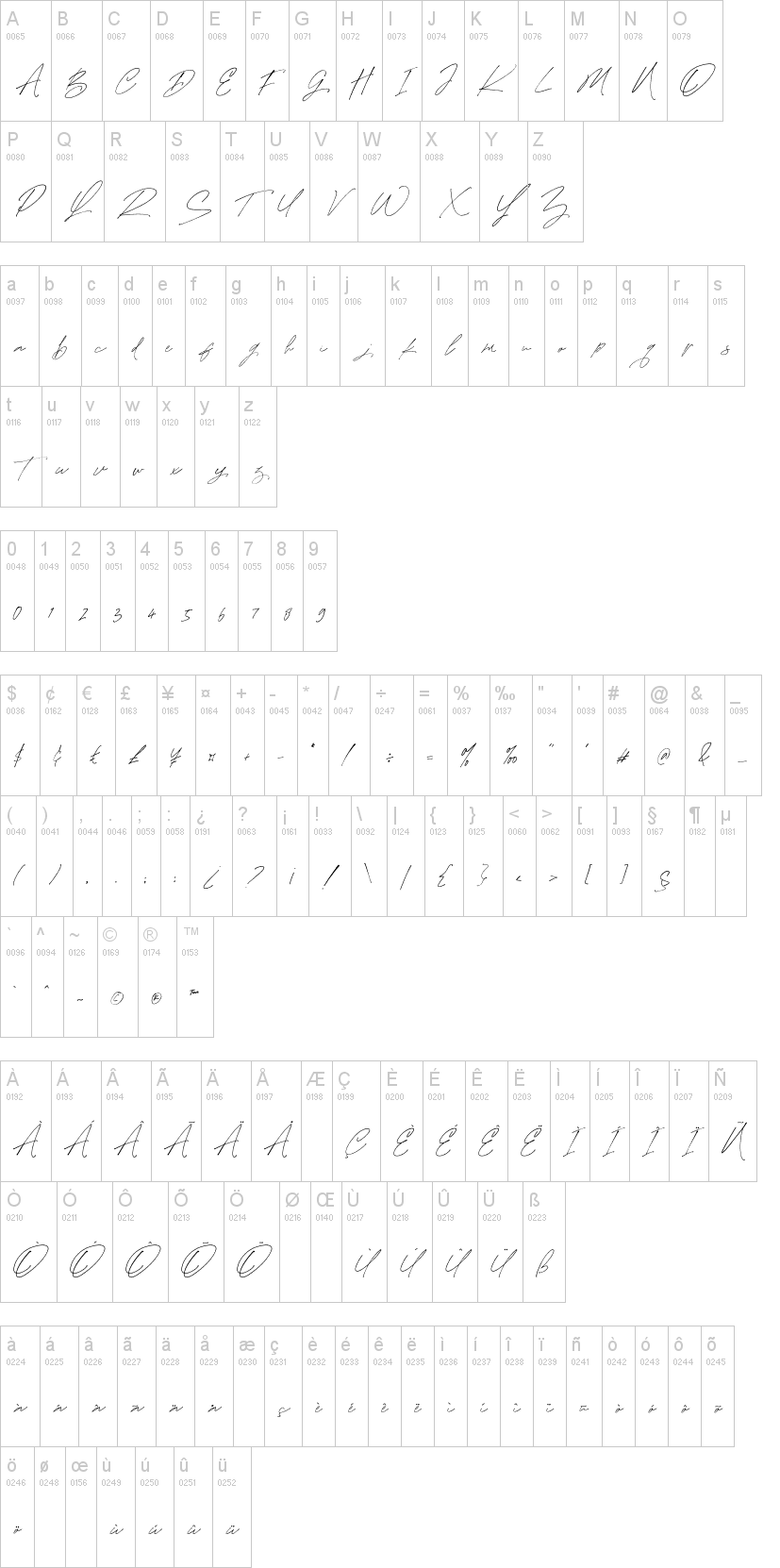
Mabrick Signature
Mabrick Signature是一种手写风格的字体。它的设计灵感来自于人类手写的特点,每一个字母都有独特的形状和笔画。这种字体的特点是优雅、舒适和自然,可用于各种场合,如品牌标志、广告宣传和印刷物等。Mabrick Signature字体采用了现代化的设计风格,同时保留了传统手写字体的特点,使其成为一种独特的字体。它的流畅性和可读性非常好,适合用于各种尺寸的设计。如果您需要一种具有个性化的字体,可以考虑使用Mabrick Signature。
Mabrick Signature是一款非常不错的手写艺术字体,具有很好的视觉感,适合于文化类的宣传设计、商业类品牌的广告和产品包装设计以及个性化文字排版等较多场景。
Mabrick Signature字符映射图